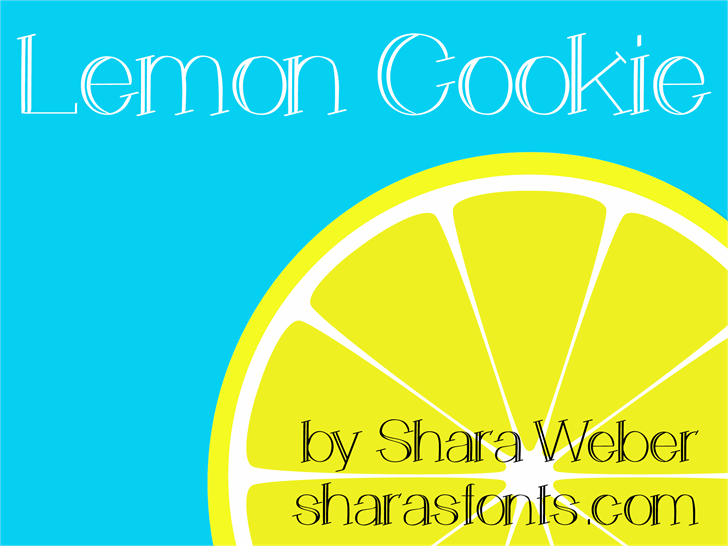
A LEMONCOOKIE Font é uma mão-dura original criada pelo designer Hamilton que irá adicionar um toque único à sua próxima projeto de design. Esta fonte não apenas oferece uma aparência suave e aconchegante, mas também traz consigo uma leve onda nostálgica através do seu traçado delicado e característico. Ideal para designers apaixonados por estilos retrô e hand-made, ela se destaca no mercado de fuentes manuscritas como um complemento perfeito ao design editorial ou personalizado. Com a LEMONCOOKIE Font, você não apenas está adquirindo uma fonte de qualidade, mas também adicionando à sua coleção algo único que pode ser usado em diversas aplicações. Seja para criar um layout minimalista e elegante, ou para dar um toque nostálgico em um design pessoal, esta fonte é perfeita. Suas formas arredondadas e traçados sutis criam uma sensação confortável e aconchegante sem perder o brilho de sua personalidade única. Como seu nome sugere, LEMONCOOKIE é como um biscoito levemente doce que acalenta ao mesmo tempo em que desperta seus sentidos, oferecendo aos designers uma fonte perfeita para aprimorar suas criações.